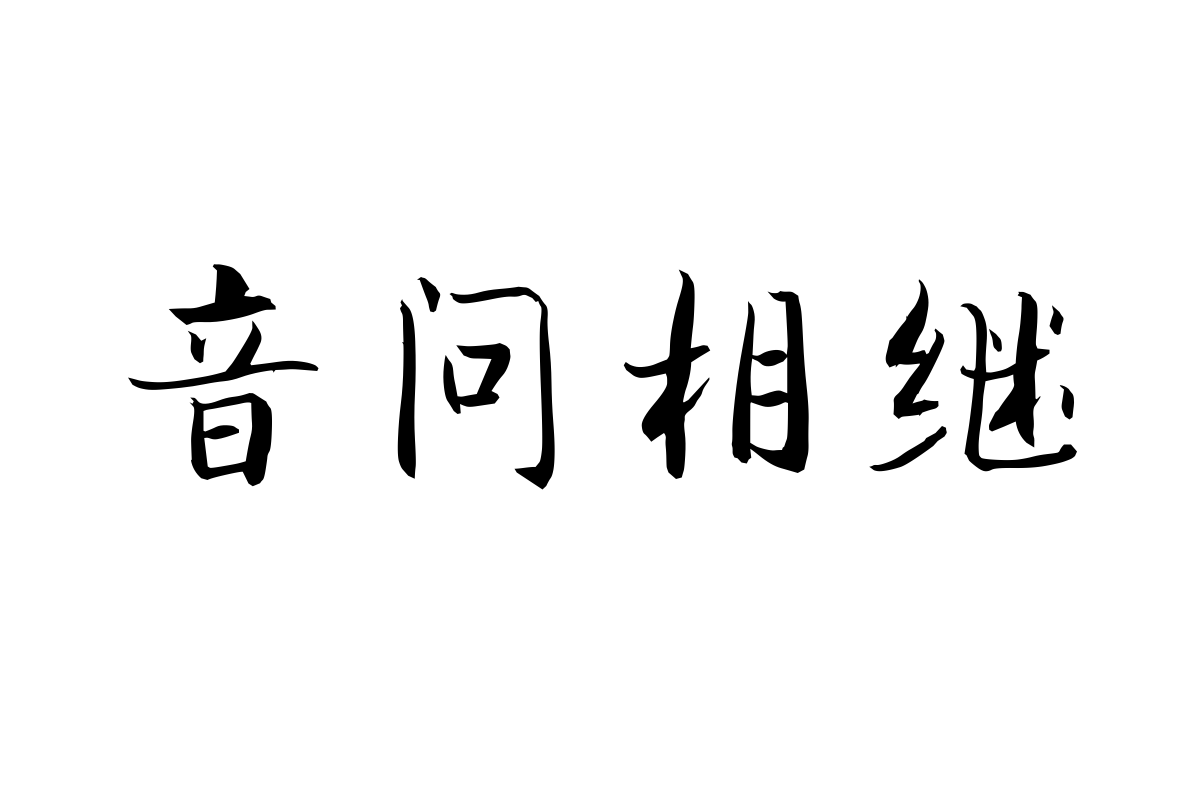
汉仪张乃仁行书简是一款由汉仪公司推出的中文手写字体,主要用于书法和艺术设计领域。这款字体的特点在于其流畅的线条和独特的结构,给人一种优雅而古朴的感觉。
1. 笔画流畅:汉仪张乃仁行书简的笔画流畅自然,没有过多的装饰性细节,使得整个字体看起来更加简洁大方。
2. 结构独特:该字体的结构独特,笔画之间的连接紧密而有力,给人一种强烈的视觉冲击力。同时,字体的大小、间距等也经过精心设计,使得整体效果和谐统一。
3. 风格古典:汉仪张乃仁行书简的风格古典优雅,适合用于书法、绘画、设计等领域,能够很好地展现出中国传统文化的魅力。
4. 适用范围广泛:这款字体适用于各种场合,如书籍、杂志、海报、包装等,能够满足不同用户的需求。
总之,汉仪张乃仁行书简是一款具有独特魅力的中文手写字体,无论是在书法还是艺术设计领域都有着广泛的应用前景。